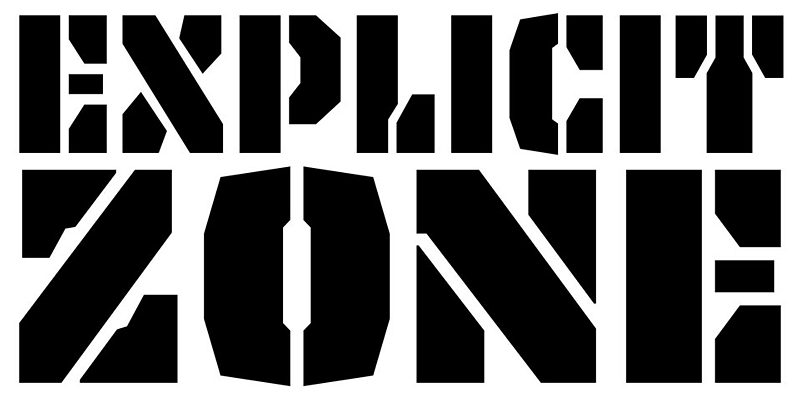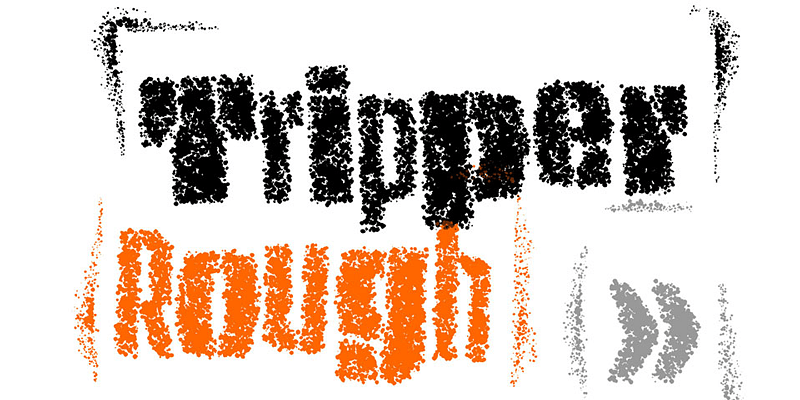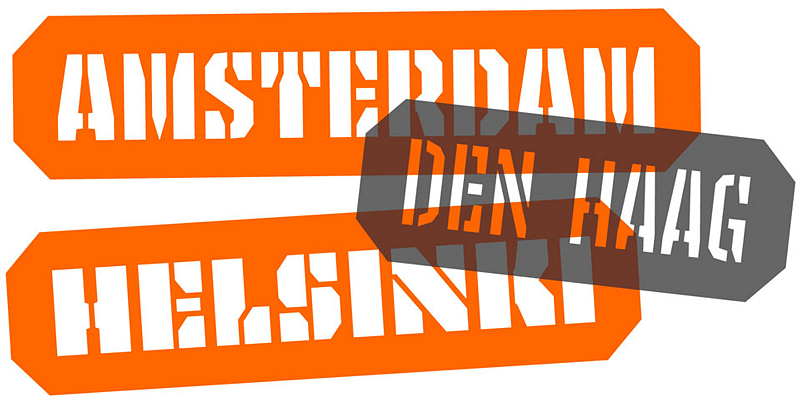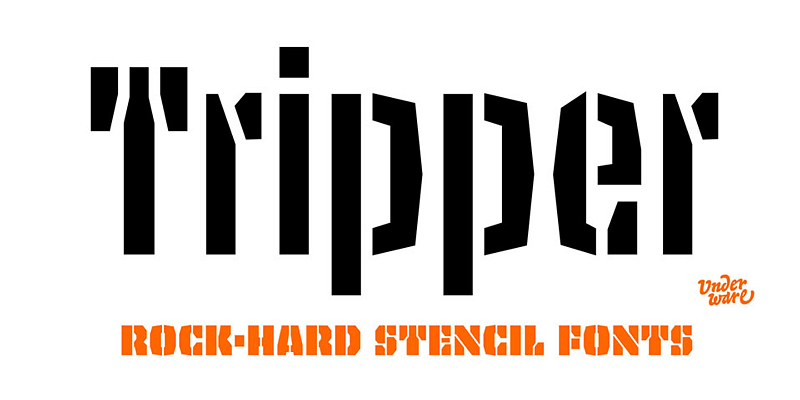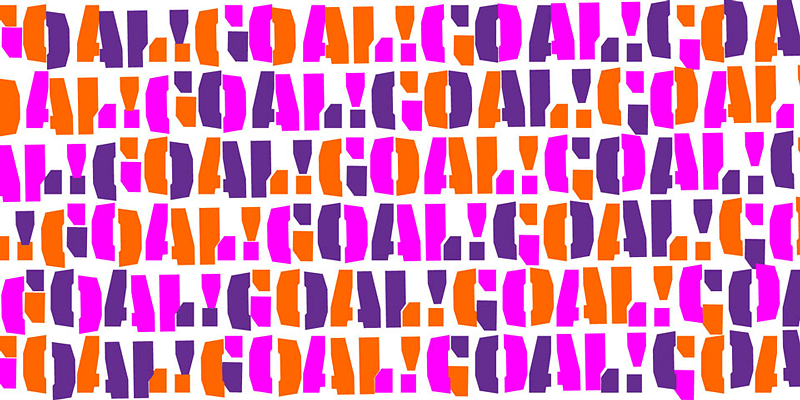
Tripper est une famille de polices d’affichage inébranlable. Les six styles, du clair au noir, de cette police robuste de style pochoir garantiront à votre texte toute l’attention qu’il mérite. Faites de Tripper un grand dans ce domaine !